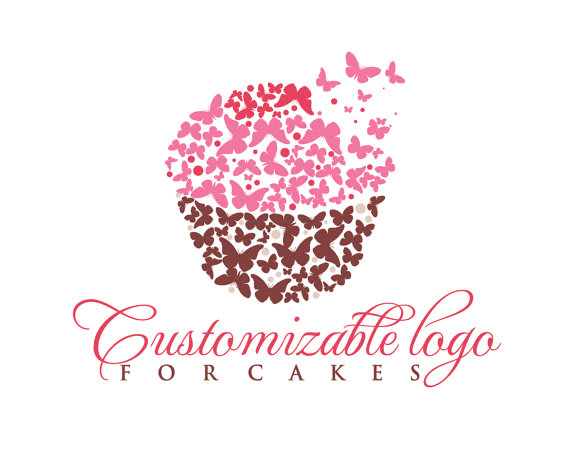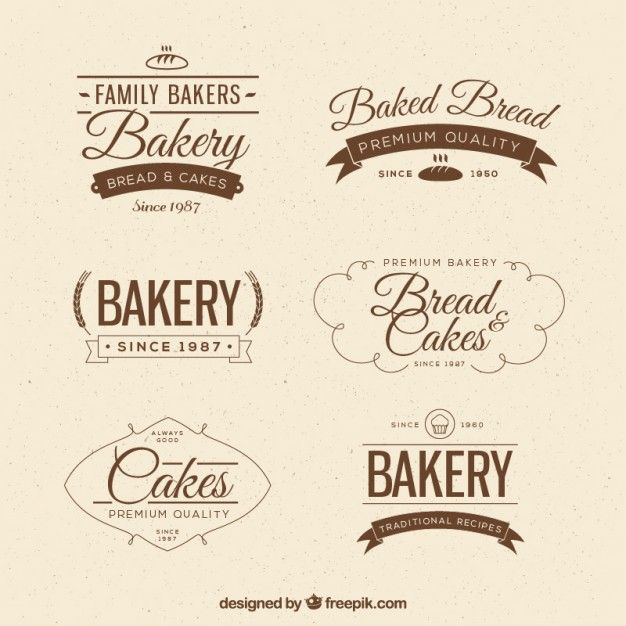
Реклама продуктов питания – дело очень непростое. В ней часто используются красочные фотографии и задача дизайнера состоит в том, чтобы представить продукт так, чтобы его изображение на упаковке максимально соответствовало тому, что находится внутри. Помимо фотографий огромную роль в фуд-дизайне играют шрифты. Как и изображение, шрифт должен в какой-то мере соответствовать характеристикам продукта, будь то кофе, мороженое или печенье.
Вот простой пример рекламы кофе. Перед дизайнером стояла задача связать кофе и европейскую культуру потребления этого напитка.
Первые кофейни появились в Австрии, поэтому шрифт подчеркнуто строгий, с тонкими штрихами и без засечек. Он вызывает ассоциации со великолепной архитектурой Вены, но не связывает кофе с вековой традицией, показывая, что кофе напиток современный, которые ежедневно пьют миллионы людей.
А вот для рекламы мороженого лучше подойдет игривый рукописный шрифт, напоминающий о детстве, когда мороженое было самым любимым лакомством. Для такого продукта, как мороженое забавные неформальные шрифты подходят как нельзя лучше, они могут быть как рукописными, так и округлыми, намекая на аморфность и позитивные ощущения при употреблении.
Как подобрать правильный шрифт?
Есть несколько факторов, которые влияют на восприятие человеком того или иного шрифта. Это форма букв, цвет шрифта, его размер, кернинг и многое другое. Есть менее очевидные факторы, которые так же играют важную роль. Шрифт должен вписываться в общий дизайн. Он должен создавать настроение и идеально соответствовать потребностям целевой аудитории.
Прежде чем начать поиски шрифта для рекламы продовольственного товара, нужно провести анализ целевой аудитории. Проще говоря, понять, какие люди будут чаще всего употреблять данный продукт. Как правило, всегда можно выяснить, кто именно является типичным клиентом. Каким, к примеру, должен быть шрифт для продукта с повышенным содержанием жира? Возьмем картофель фри, в котором количество жиров составляет 25,9%. Возможно, это человек, который любит есть данный продукт, запивая его пивом или газировкой. А может быть это семья с маленькими детьми, которая остановилась перекусить в небольшом придорожном кафе. В зависимости от аудитории и стратегии продвижения по рынку, шрифт для рекламы картофеля фри может быть разным, но при этом желательно, чтобы он не был слишком строгим.
Пицца-шрифты
Пицца, а также гамбургеры и сэндвичи – это классический фастфуд. В рекламе этих продуктов существуют давние традиции, история фастфуда началась в 60-х годах ХХ века, поэтому здесь вполне будут уместны винтажные шрифты. Однако фантазия дизайнера ничем не ограничена, можно составить другой ассоциативный ряд: пицца круглая, колбаса пепперони тоже круглая, следовательно, можно использовать округлые шрифты.
Шрифты для рекламы пиццы, бургеров, сэндвичей
- Hot Pizza Font
- Mom’s Diner Font
- Snappy Service NF
- Caesar Little SS Font
- Skittles n Beer NF Font
- Guinness Extra Stout NF Font
- Pilsen Plakat Font
- Rialto NF Font
- Insaniburger Font Family
- CHEESE PIZZA Font
- Buffalo Chicken font
Шрифты для рекламы пива
Подбирая шрифт для рекламы такого продукта, как пиво, нужно обязательно учитывать контекст.
Как и в случае с фастфудом, есть некие неписаные шрифтовые каноны и нужно выстроить ассоциативный ряд так, чтобы шрифт идеально отвечал потребностям аудитории. Если продукт каким-то образом связан с европейской культурой, то неплохим выбором будут готические шрифты. Готика напоминает о баварских и чешских пивоварнях, которые, так уж повелось, считаются лучшими производителями пенного напитка. Но не обязательно шрифт должен быть «под старину», существует множество производителей современных сортов пива, которые позиционируют себя совершенно иначе. В зависимости от позиционирования, шрифт может быть винтажным, неформальным или каллиграфическим. Он может быть каким угодно, как с засечками, так и без, важно лишь, чтобы он вписывался в контекст.
«Пивные» шрифты
- Traditio AH Font
- College Block Font
- Ring of Kerry Font
- Pilsen Plakat Font
- Rialto NF Font
- Mastodon Font Family
- Anchor Steam NF Font
Шрифты для рекламы сладостей
Сладкое любят все, однако основная целевая аудитория таких продуктов, как конфеты, печенье, мороженое и многое другое – это дети.
И даже если это взрослые, нужно помнить, что каждый взрослый в душе немного ребенок, а значит шрифт для сладких продуктов должен быть не слишком формальным. Шрифт должен вызывать ассоциации с продуктом, поэтому ассоциативный ряд будет примерно таким: продукт сладкий, вкусный, сочный, клейкий, тянущийся, холодный. То есть нужно описать его признаки и уже на основе этих характеристик подбирать шрифты. Как известно, существуют шрифты, идеально подходящие для детской аудитории. Как правило, это рукописные или неформальные шрифты с различной толщиной штриха. В рекламе сладостей также нужно обращать внимание на цвет шрифта – он должен перекликаться с внешним видом продукта. Для такого продукта как мороженое лучше подойдут холодные оттенки, а для леденцов, наоборот, теплые.
«Сладкие» шрифты
- Bittersweet NF Font
- Apple Butter Font
- Chicken Hut Font
- KR Frosted Cake Font
- Caesar Little SS Font
- Soft Marshmallow Font
- Breakfast DEMO Font
Шрифты для кондитерских изделий
Существует огромное количество самых разных кондитерских изделий.
Создание продуктов на основе теста это большое искусство, поэтому шрифт должен ассоциироваться с запахом и вкусом выпечки. Нужно также учитывать, так сказать, бэкграунд продукта: шрифт для рекламы маффина будет отличаться от шрифта для рекламы пряника. В чем нет сомнений, так это в том, что шрифт должен быть позитивным, приятным на вид и вызывающим положительные ассоциации. И, конечно, нельзя забывать о характеристиках продукта. Составляя ассоциативный ряд нужно помнить о культуре потребления продукта, его истории, форме, начинке и многом другом.